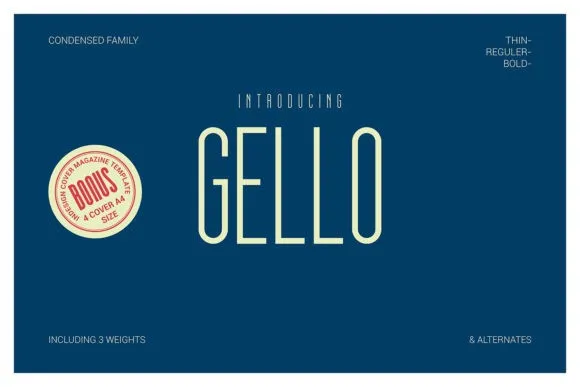
Gello Font Family – Download Grátis
A Gello Font Family é uma elegante tipografia sans-serif geometrica criada pela Line Creative. Esta fonte transmite uma impressão sóbria e simpática ao mesmo tempo, graças aos ângulos arredondados que acalmam os olhos. Mesmo sua aparência simples não a torna fraca; pelo contrário, ela é mais do que suficiente para capturar e manter o interesse de quem a vê. A Gello Sans Family foi projetada especialmente para tipos sans-serif, caracterizada pela sua slimness (delicadeza) e altura. Isso conferindo uma impressão de limpeza e extremamente elegante. Ela é perfeitamente adequada para usar como headlines, posters, títulos em outras aplicações gráficas. A Gello possui três variantes: Thin, Regular e Bold, garantindo a você a flexibilidade necessária para adaptar à sua necessidade de design.